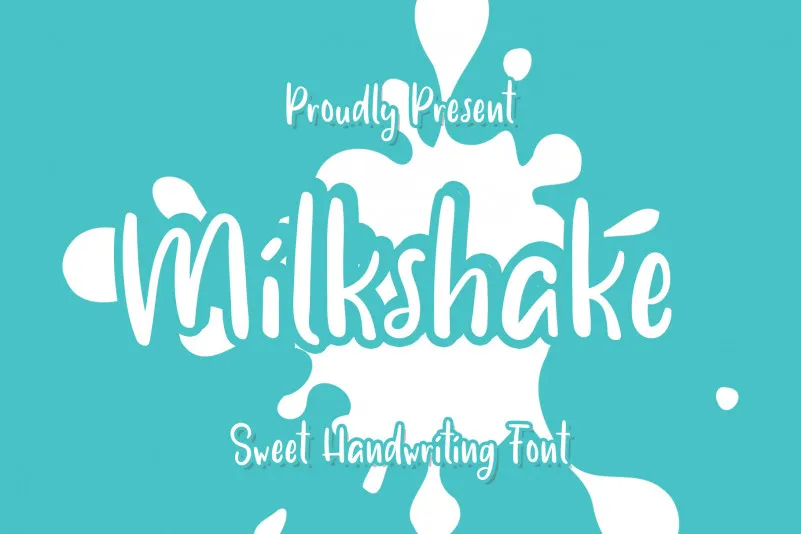
Milk shake Font – Fonte Grátis
Milk shake Font
Aqui está uma versão em português do Brasil, envolvente e natural, para a descrição de uma página de download da fonte ‘Milk Shake Font’, categorizada como Script Fonts: ‘Sweet e simples, com um toque caramelo de personalidade. A Milk Shake Font é perfeita para aqueles momentos delicados e únicos que merecem um toque único. Este script fluido encaixa-se em uma variedade de ideias de design, desde o crafting até as apresentações elaboradas ou os cards de agradecimento. Suave como sua primeira bebida de sorvete, esta fonte vai fazer seu projeto brilhar de maneira única e envolvente.’ Esta descrição mantém a essência da original em inglês, enfatizando o aspecto suave, simples e personalizável desta fonte script. Ela também menciona aplicabilidades para diversas áreas do design sem repetir o nome da fonte.